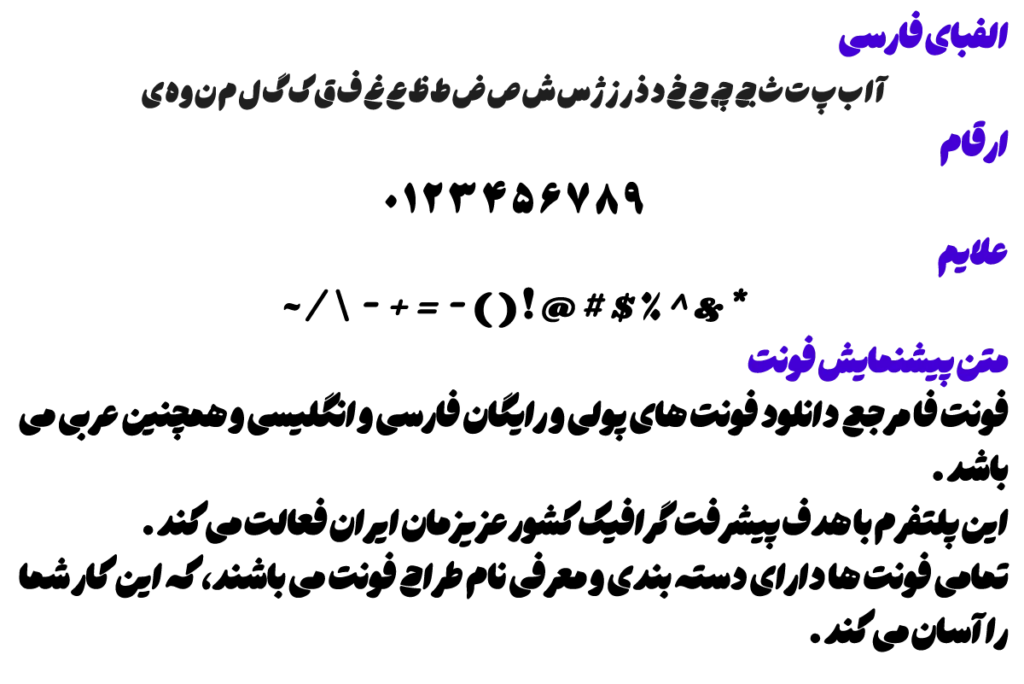
پیشنمایش فونت هستی
فونت فارسی هستی - Hasti
توضیحات و معرفی فونت هستی
فونت فارسی هستی ( Hasti ) از مجموعه فونت های برتر و پولی می باشد، همچنان نوع فونت دست نویس و عنوان می باشد.
فونت شگفت انگیز و زیبای فوق توسط مسلم ابراهیمی در سال 1402 طراحی و ساخته شده است.
فونت هستی، ترکیبی هنرمندانه از دو سبک نوشتاری نسخ و نستعلیق است.
این فونت، هرچند از نظر طراحی منحصربه فرد است و شباهتی به فونت های قبلی ندارد که به خوبی حس متفاوت بودن ایجاد می کند.
دلیل این ارتباط موثر، شباهت های ظریف آن به نستعلیق می باشد که به عنوان کلید اصلی برقراری این پیوند شناخته می شود.
تصویر زیر نوشته شده با تایپ فیس مربوط می باشد.
فونت فارسی هستی - Hasti
نسخه جدید این فونت دارای دو سبک گرد Rounded و تیز Sharp و نقطه کلاسیک و گرد است.